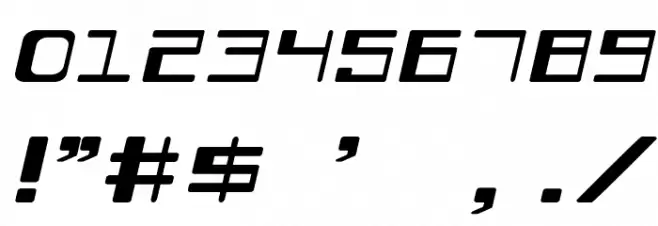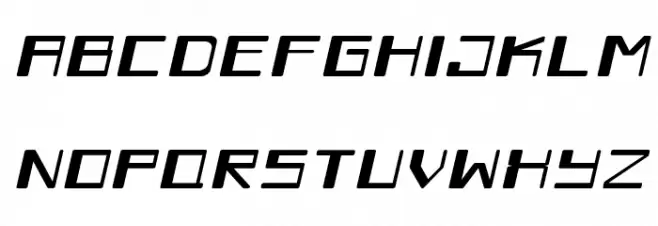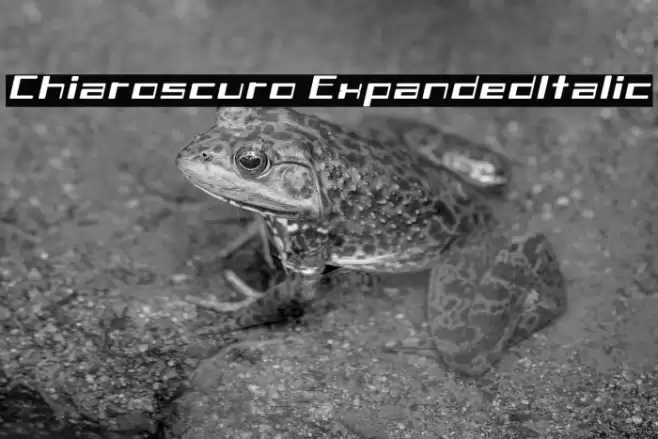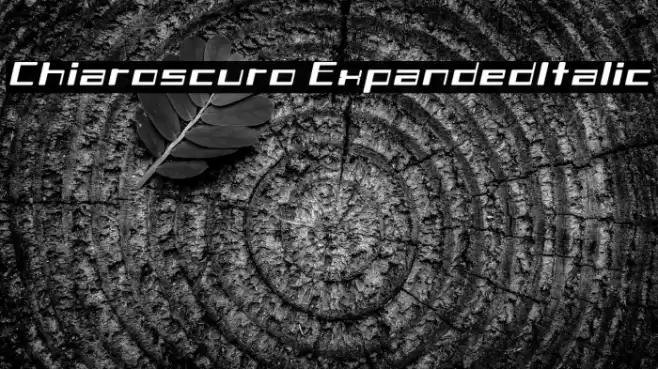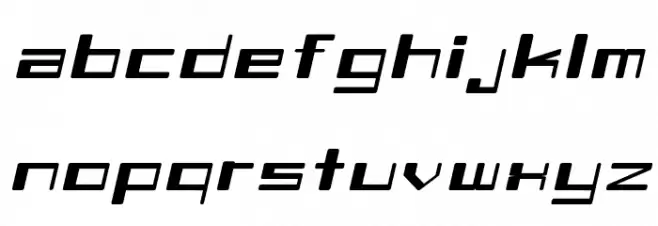
Chiaroscuro-ExpandedItalic Font
| Cas d'utilisation | Headlines, Logos, Branding |
| Projets proposés | Ideal for branding, advertising, and editorial design projects that require a modern and dynamic touch. |